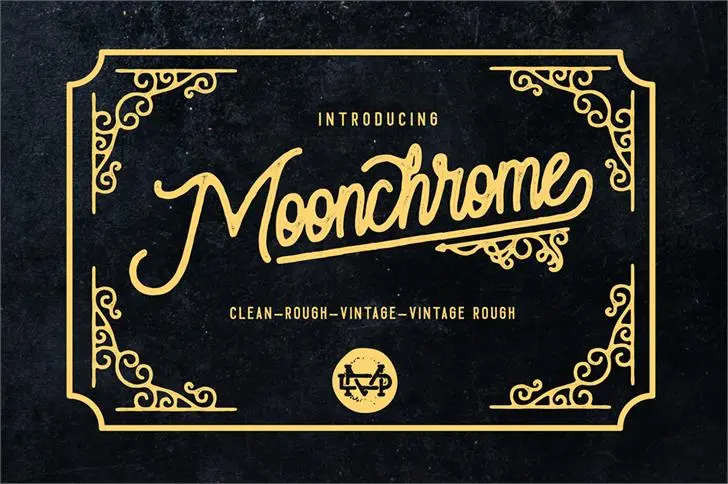
Moonchrome Typeface – Download Grátis
A fonte Moonchrome Typeface é perfeita para projetos visuais criativos, com 4 variações alternativas que permitem uma grande liberdade na criação. Essa fonte monoline se destaca por seu design limpo e elegante, projetada especialmente para aplicação em posters, capas de livros, merchandising, campanhas fashion, newsletters, marca identidade, anúncios, revistas, cartões de agradecimento, capas de álbuns, entre outras utilizações visuais. Ideal tanto para designers gráficos quanto para pessoas que buscam uma fonte única e poderosa para expressar seu trabalho em um formato único, Moonchrome Typeface oferece a você o poder de criar experiências sensoriais diferenciadas em seus projetos. É perfeitamente adaptada para qualquer tipo de projeto visual onde deseje destacar sua marca ou mensagens visuais de uma maneira elegante e inovadora.